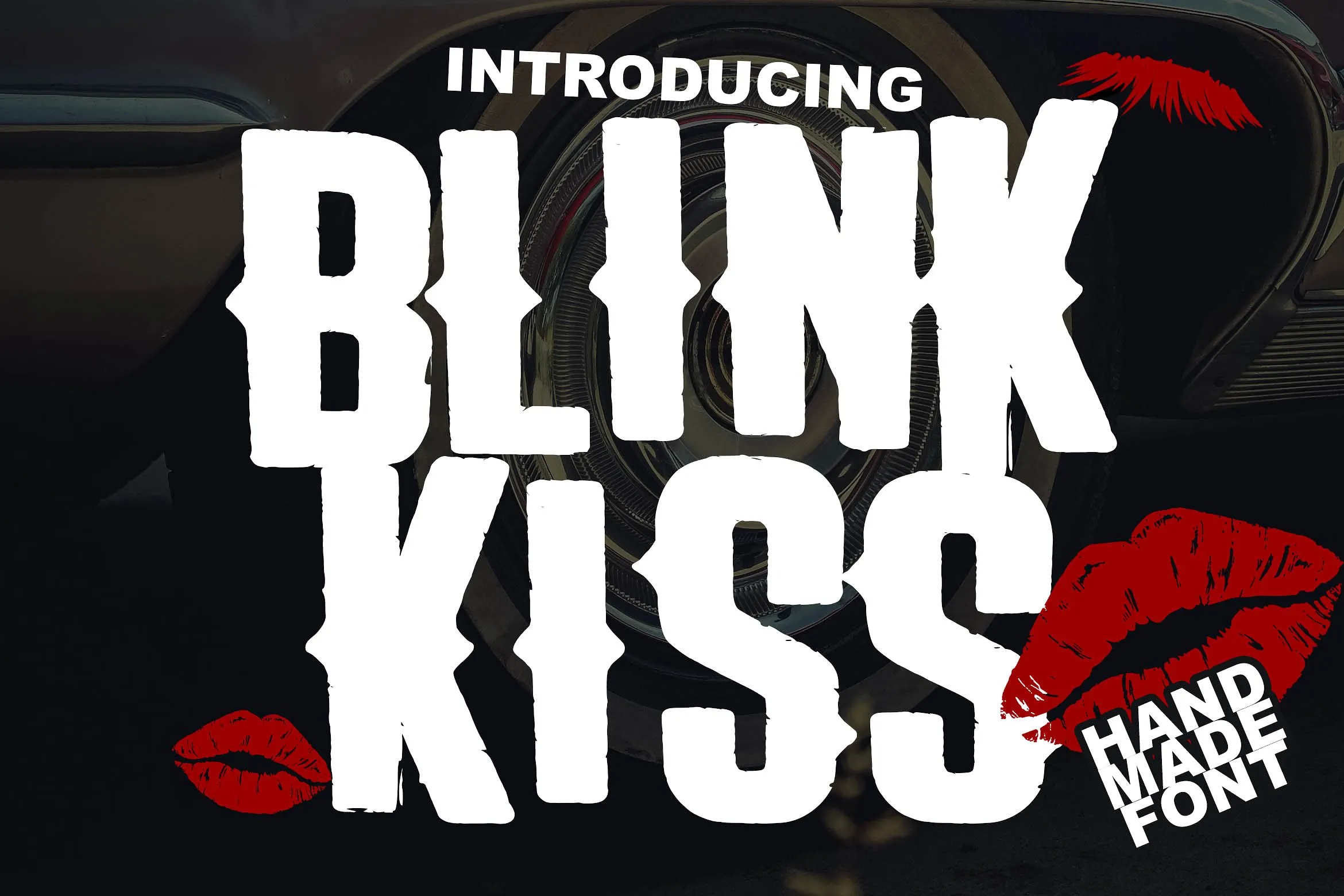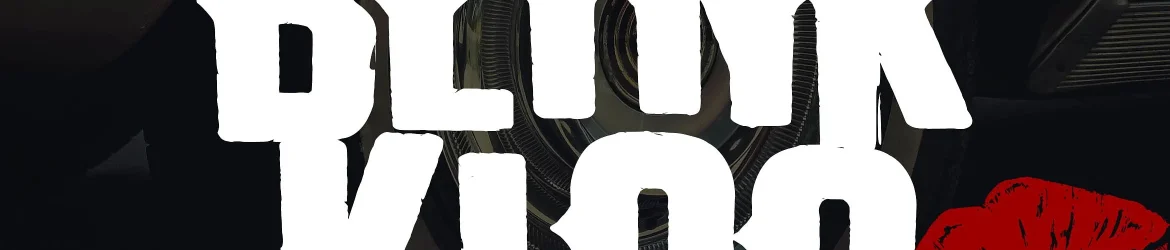
A fonte “The Blink Kiss Logotype Font” é uma fonte de display compacta com texturas distintas para cada letra. Ela oferece um toque rústico que se adequa perfeitamente ao design de embalagens de whisky, mas seu uso é vasto e poderoso em muitos outros projetos gráficos. Esta fonte única foi criada pelo designer Lettersiro e está disponível para sua utilização em logotipos, frases, outdoors, letra engraçada, roupas ou qualquer projeto de design. Com texturas únicas em cada caractere, este é o tipo perfeito para quem busca uma mistura assertiva entre elegância e rusticidade. Suas letras grossas e estilizadas fornecem um toque moderno que se assemelha a logotipos icônicos de marcas distinta ou celebridades. Ela oferece flexibilidade suficiente para ser usada em várias aplicações, desde o design de adesivos de celular até as etiquetas da sua loja local. O designer M.0Type criou uma fonte ideal para quem busca uma sensação atemporal e sofisticada para seus projetos, mas ainda manter um ar jovial que se adequa perfeitamente ao seu estilo personalizado. Sempre lembre de usar o “Uppercase” (maiúsculas) ou o “Lowercase” (minúsculas) conforme necessário para garantir a elegância e a consistência do design.